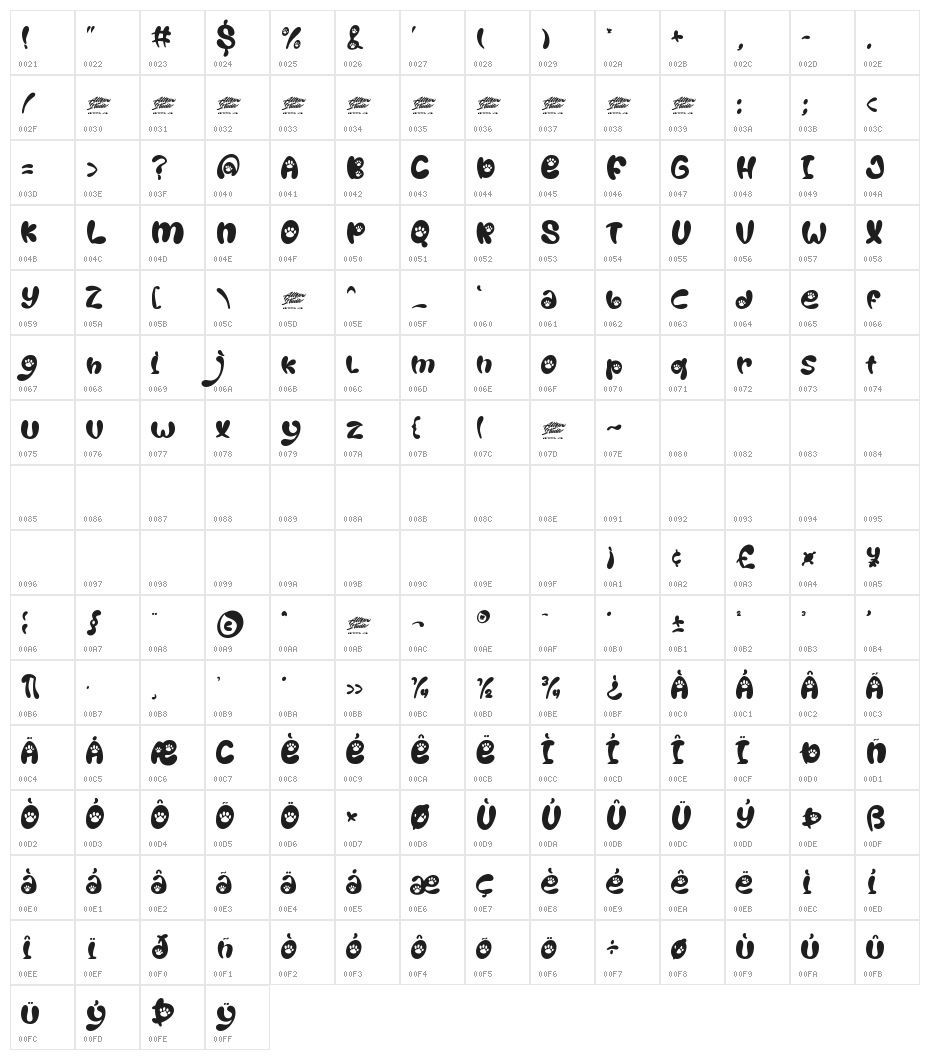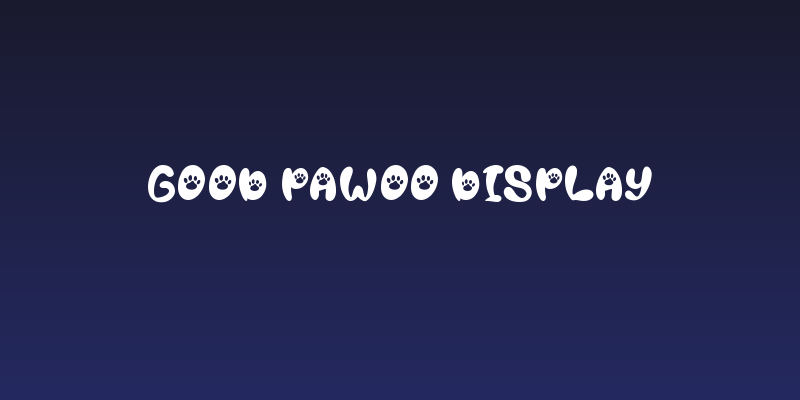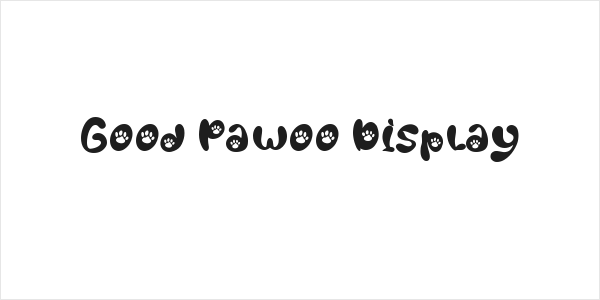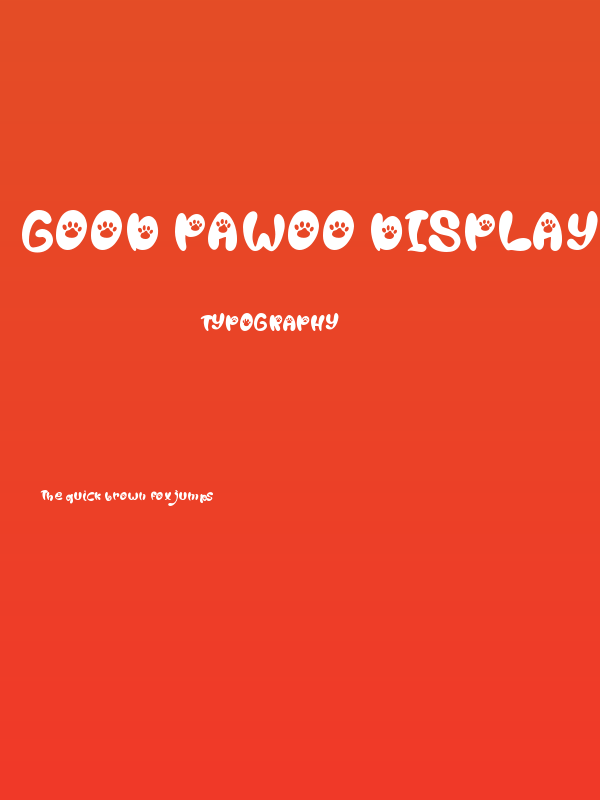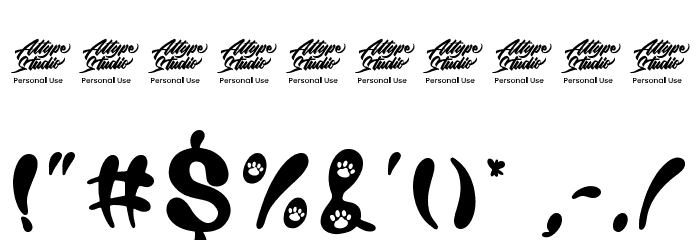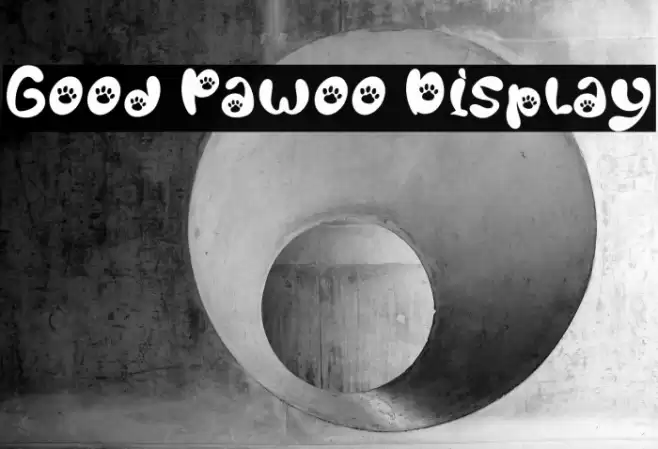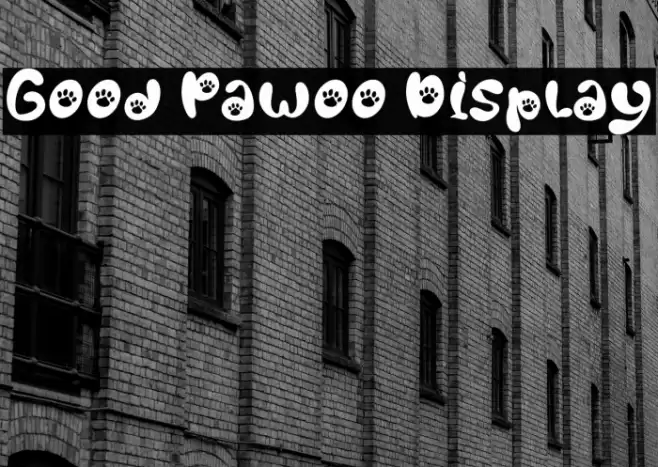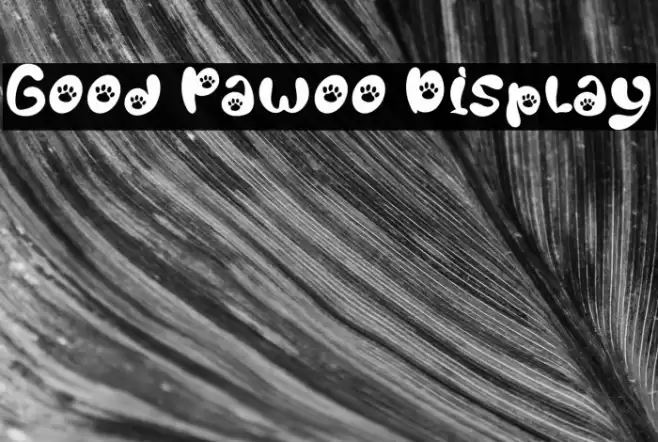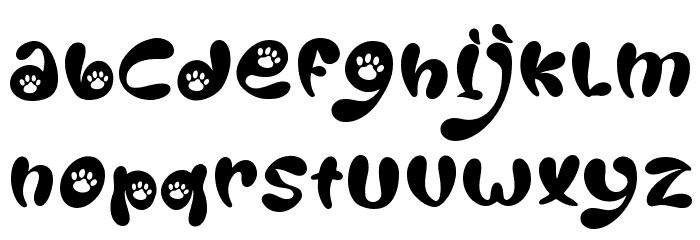
Good Pawoo Display Font
| النمط العام | Playful |
| حالة الاستخدام | Logos, Posters, Children's books |
| مشاريع مقترحة | Ideal for pet-related branding, children's books, playful posters, and greeting cards. |